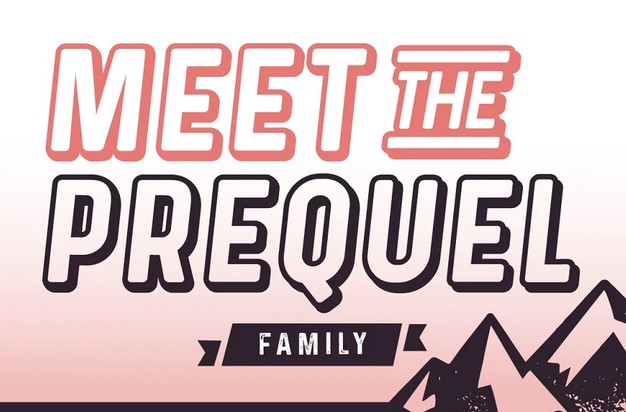
[Creativemarket] Prequel Shadow Font
Год назад я создал свой самый первый шрифт Sequel, который до сих пор много значит для меня, потому что этот шрифт открыл мне мир шрифтового дизайна. Я всегда хотел создавать новые стили для уникального дизайна. Теперь я наконец-то сделал это, но со всем моим опытом, который я получил за прошедший год, у меня также появилось желание изменить некоторые вещи. Поэтому я решил переработать его в совершенно новое, переработанное семейство шрифтов - с множеством совершенно новых букв, множеством улучшений, меньшей высотой x и лучшим кернингом.